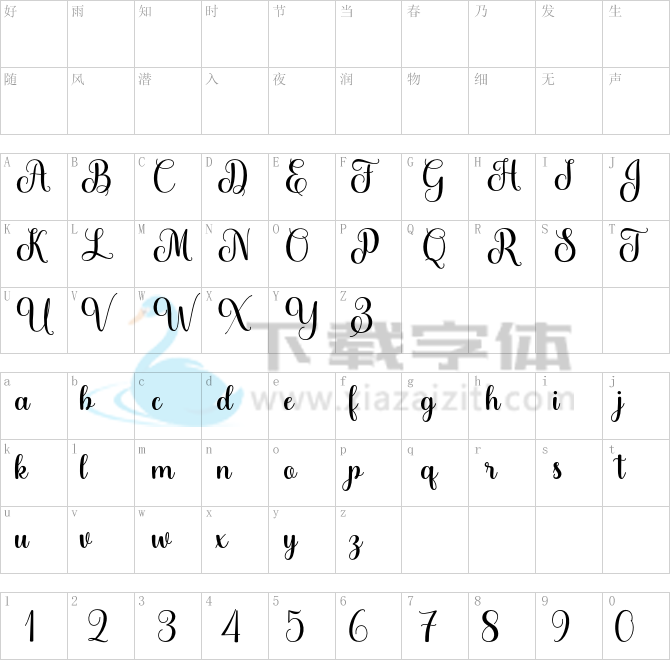
Aellena.otf字体下载,这款字体结构工整、笔画清晰,兼顾美观与易读性,适用于标题、正文、海报、包装、LOGO 等多种场景。字形优雅稳定,风格百搭耐看,适配日常排版与创意设计,让文字呈现更舒适、更具质感。Aellena.otf字体下载一笔一画,皆是细节,以均衡的比例、流畅的线条打造舒适视觉体验,字形端正大气,风格简约现代。无论是商业设计、品牌宣传还是日常排版,都能轻松驾驭,让文字更有格调与力量。Aellena.otf字体下载字体下载。